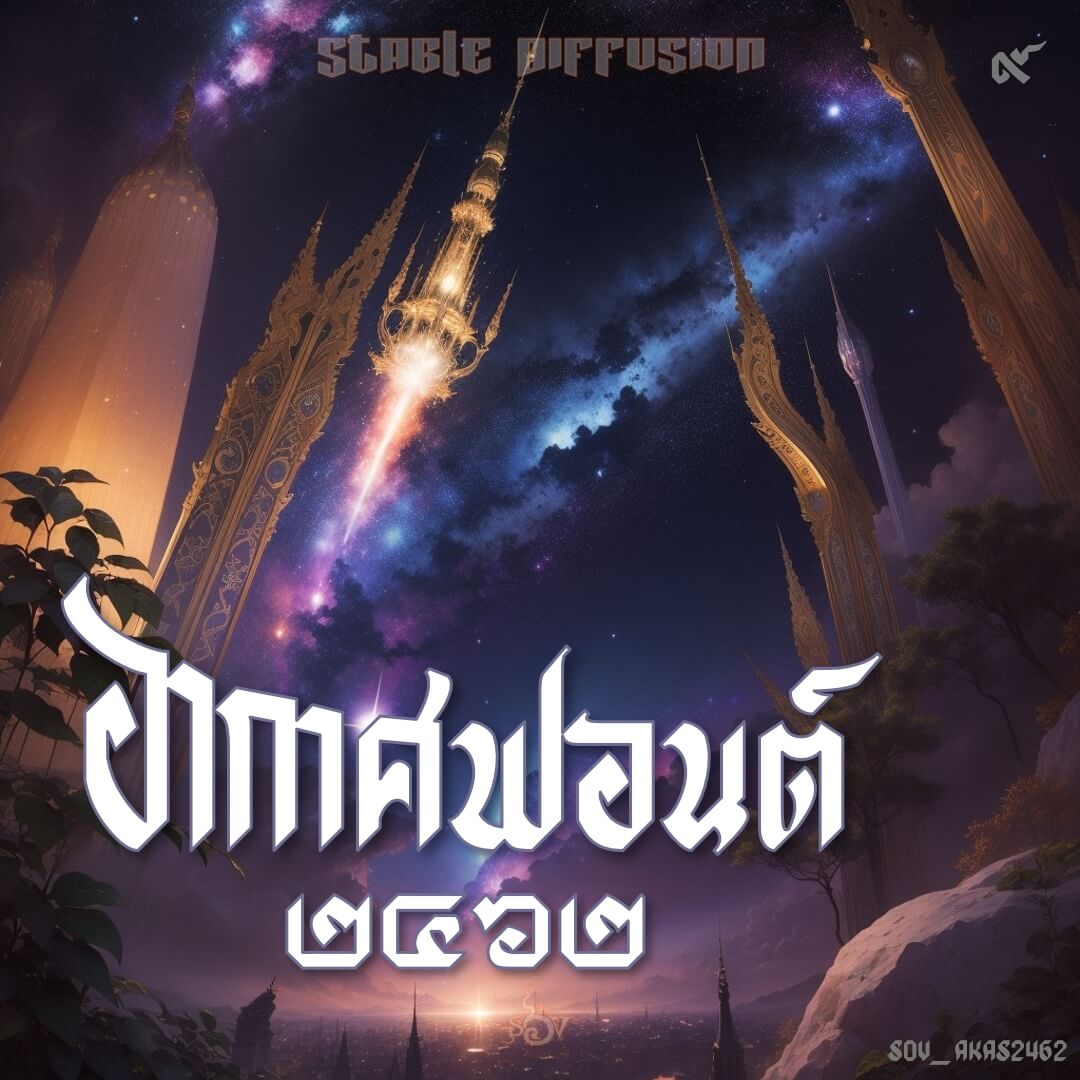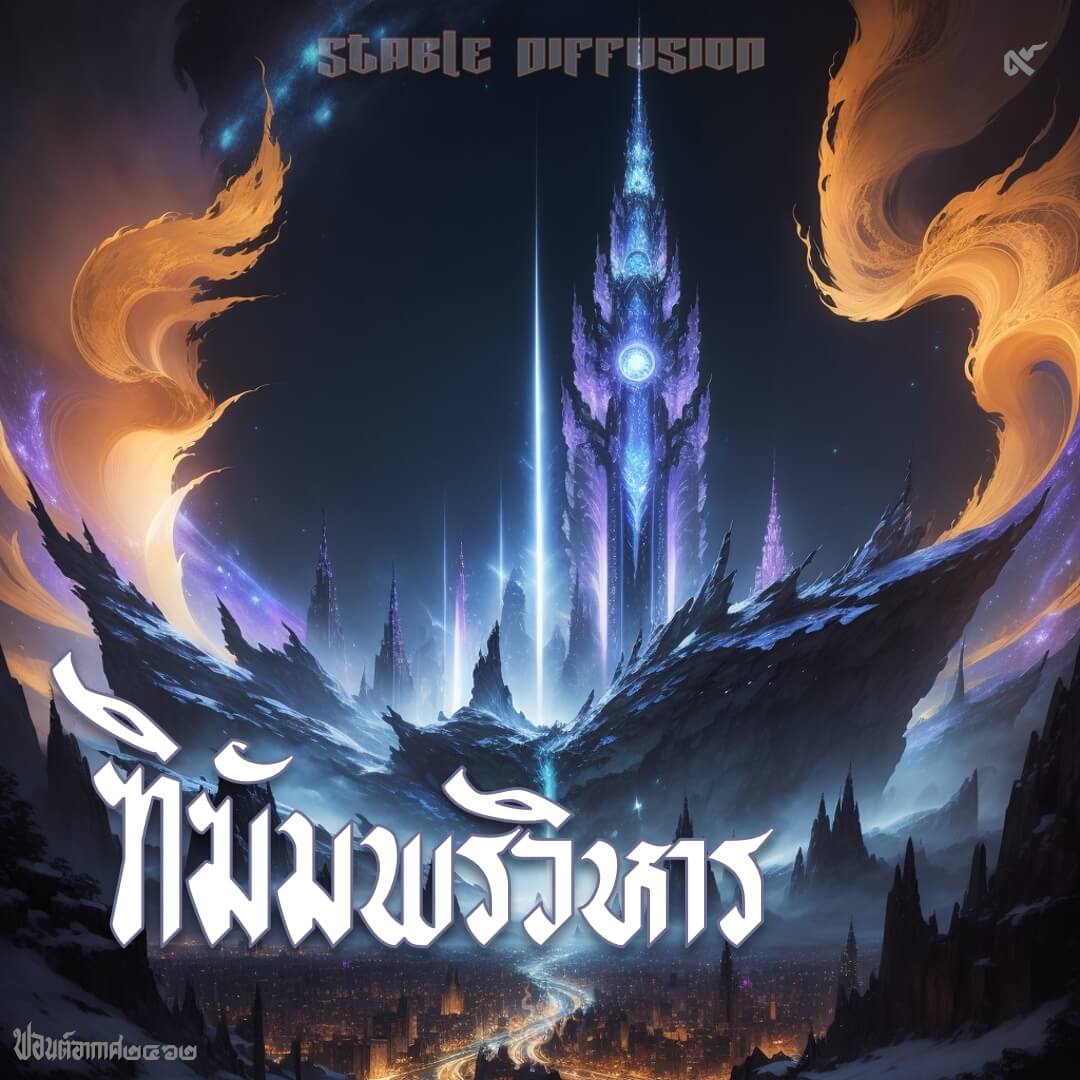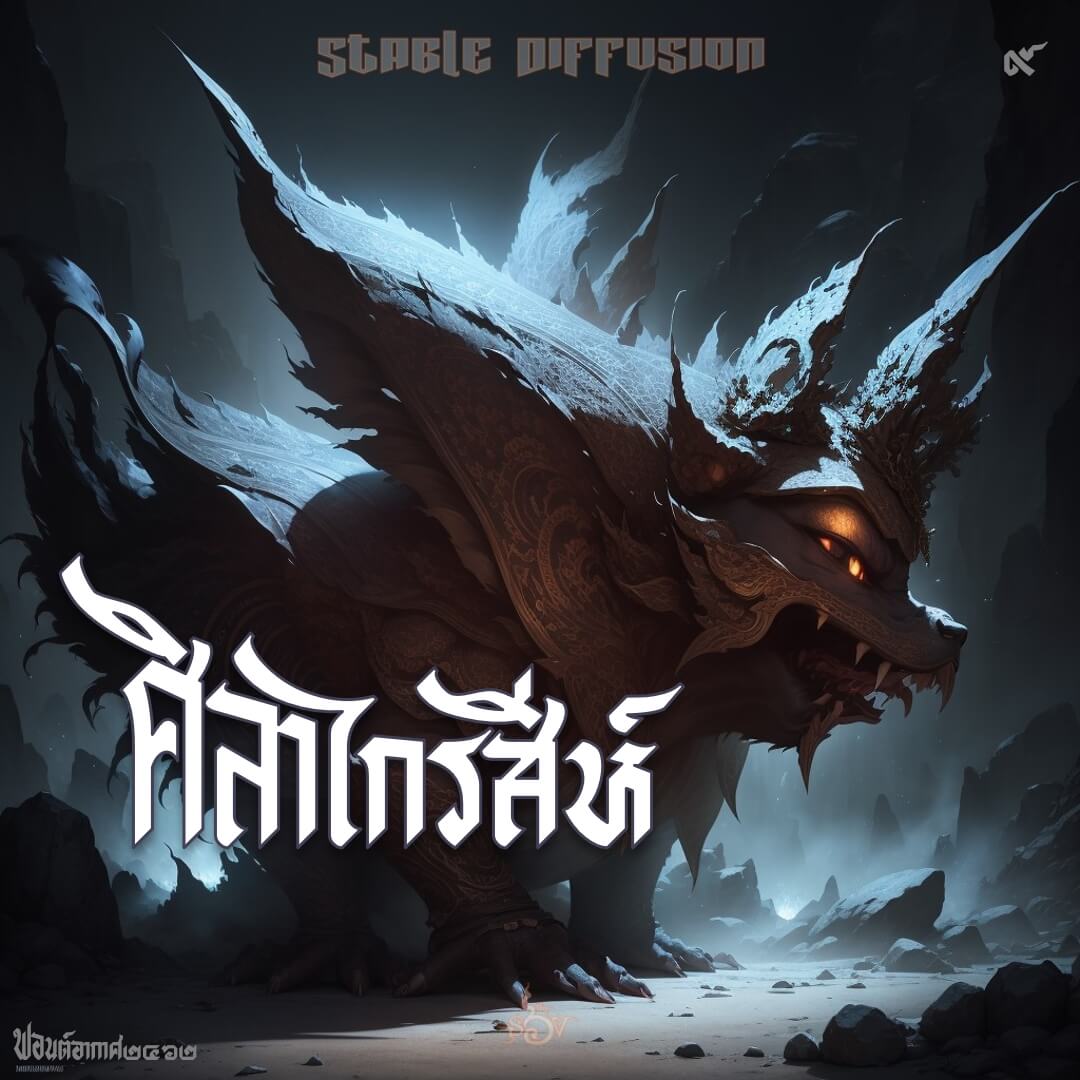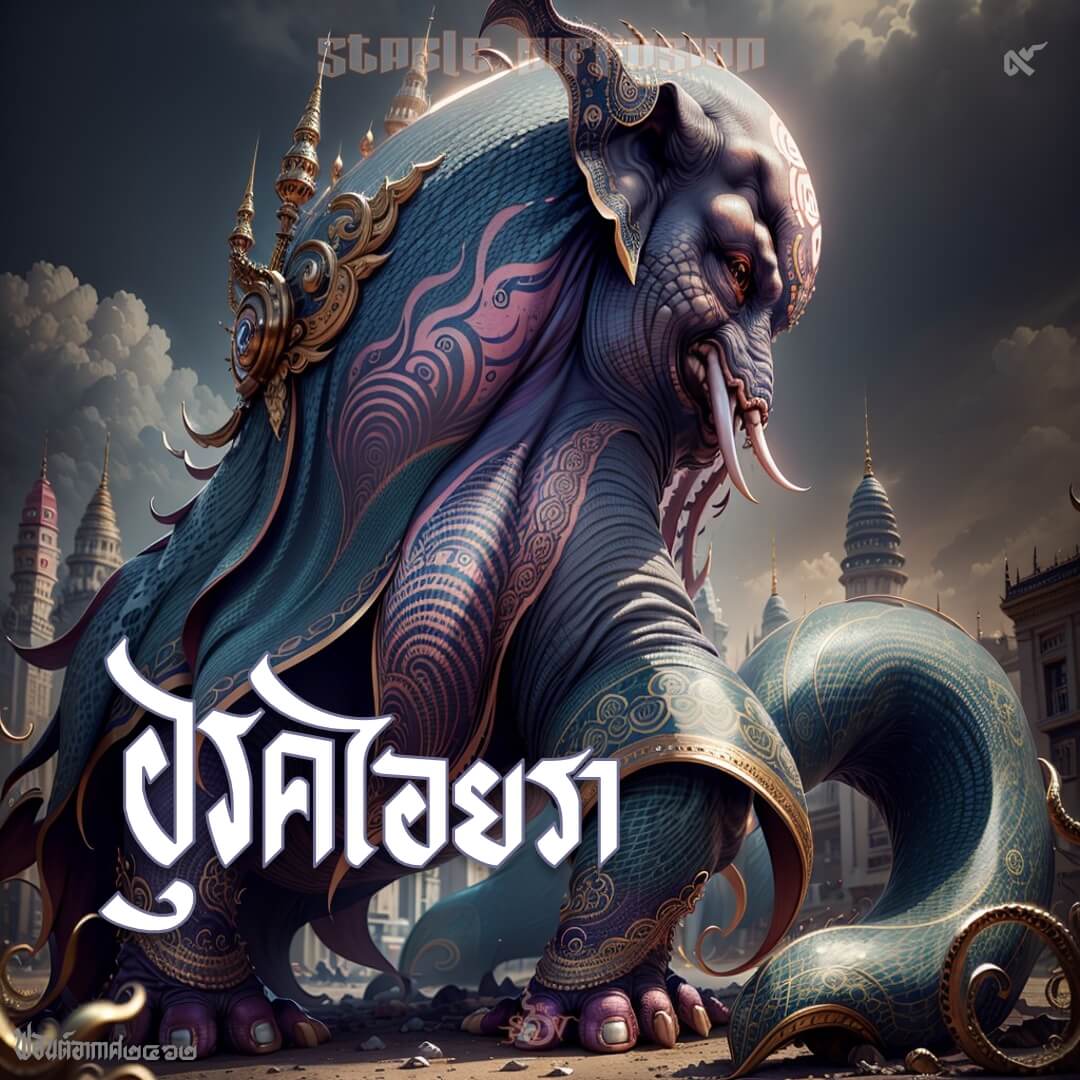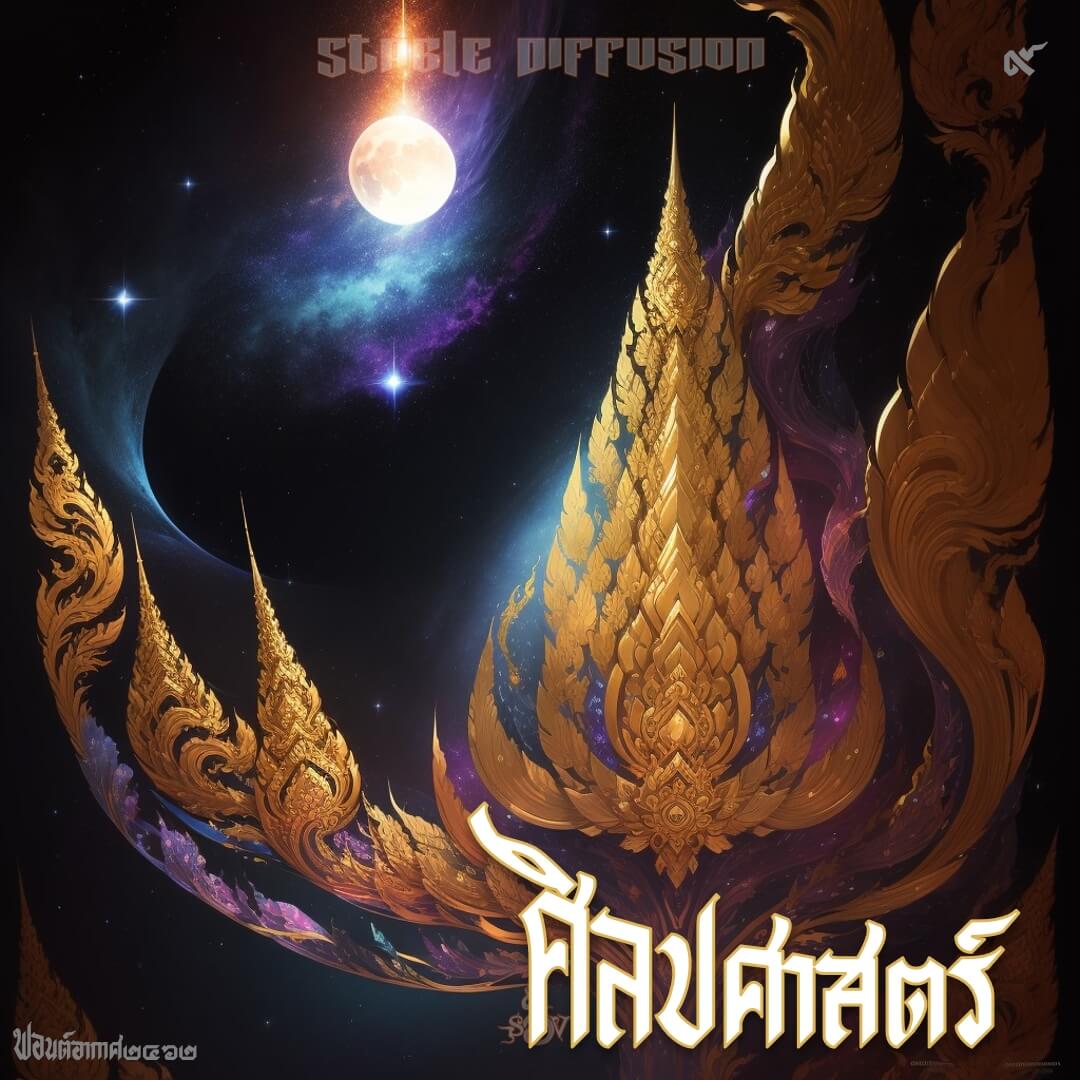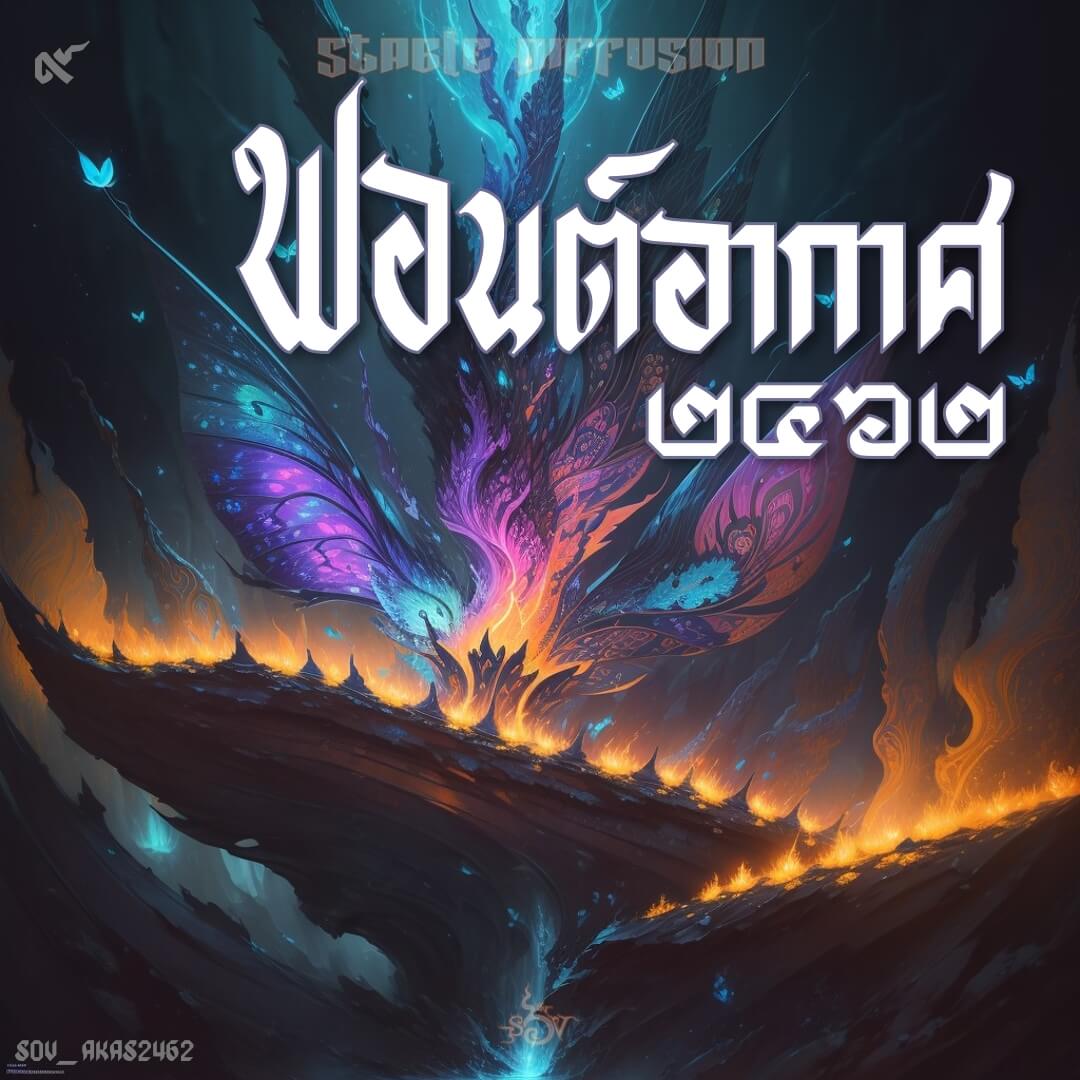
ฟอนต์อากาศ๒๔๖๒ ต้นทางจากแสตมป์อากาศไปรษณีย์ (air-mail) เมื่อปี พ.ศ.๒๔๖๒ เป็นฟอนต์พาดหัว ที่เหมาะจะอยู่ด้านล่าง
เบื้องหลังการออกแบบ : ฟอนต์ อากาศ๒๔๖๒
อากาศ๒๔๖๒ (SOV_Akas2462)